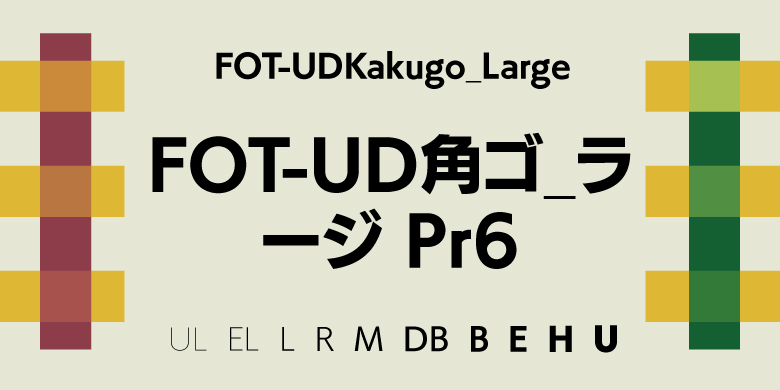
FOT-UDKakugo_Large家族
FOT-UDKakugo_Large家族,这款字体结构工整、笔画清晰,兼顾美观与易读性,适用于标题、正文、海报、包装、LOGO 等多种场景。字形优雅稳定,风格百搭耐看,适配日常排版与创意设计,让文字呈现更舒适、更具质感。FOT-UDKakugo_Large家族一笔一画,皆是细节,以均衡的比例、流畅的线条打造舒适视觉体验,字形端正大气,风格简约现代。无论是商业设计、品牌宣传还是日常排版,都能轻松驾驭,让文字更有格调与力量。FOT-UDKakugo_Large家族字体下载。
字体品牌: Fontworks 设计师:Fontworks 字体分类:黑体 字体属性:外文 字符集:Unicode 发布时间: 2024
“新罗丹”是一种非常现代的黑体,特别适用于标题等。这款 UD黑体 lardge在保持汉字和假名(かな)几乎相同大小的特点的基础上,为了提高视觉识别性和区分性,更改了英数字的字体设计。此外,对一些较粗字重的浊点和半浊点进行了调整。